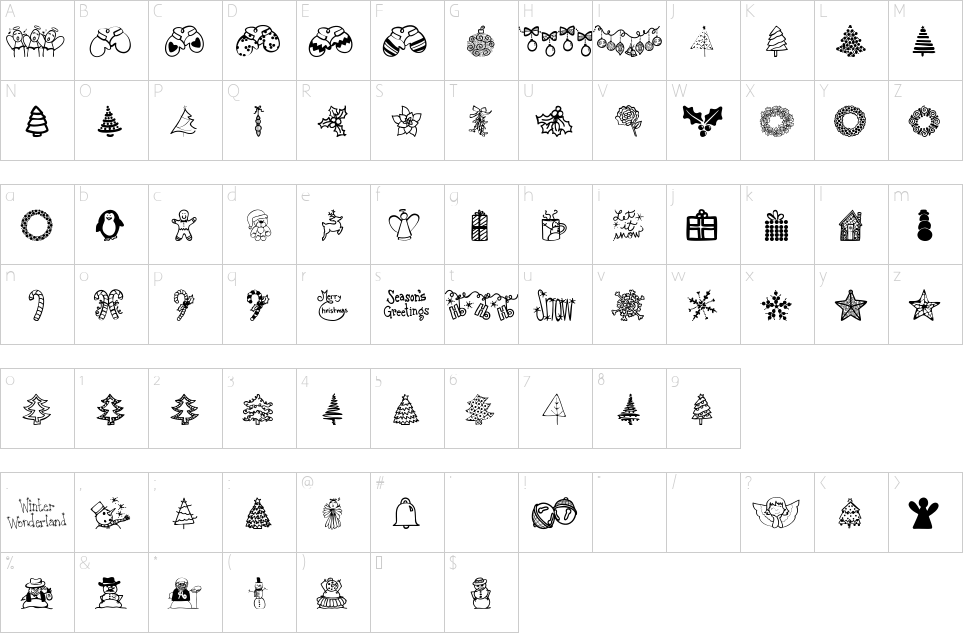
Austie Bost Christmas Doodles Font – Fonte Grátis
Austie Bost Christmas Doodles Font
Austie Bost Christmas Doodles é uma fonte encantadora criada pelo designer Austie Bost Fonts. Inspirada na magia do Natal, essa fonte pode transformar qualquer texto em uma obra de arte que ecoa o espírito natalino. Descubra como esta fonte única pode personalizar seus designs de Natal e aniversários de forma única. Com design delicado e detalhado, ela é ideal para criar frases de Natal, adesivos natalinos, cartões de aniversário, ou simplesmente decorar seus documentos digitais com um toque de magia. Esta fonte foi baixada mais de 73.339 vezes e é uma escolha perfeita para designers que valorizam a criatividade e a personalização. Se você está procurando por uma fonte de natal de alta qualidade, Austie Bost Christmas Doodles é a escolha certa para adicionar um toque especial a seus projetos.
Mapa de caracteres da fonte Austie Bost Christmas Doodles Font